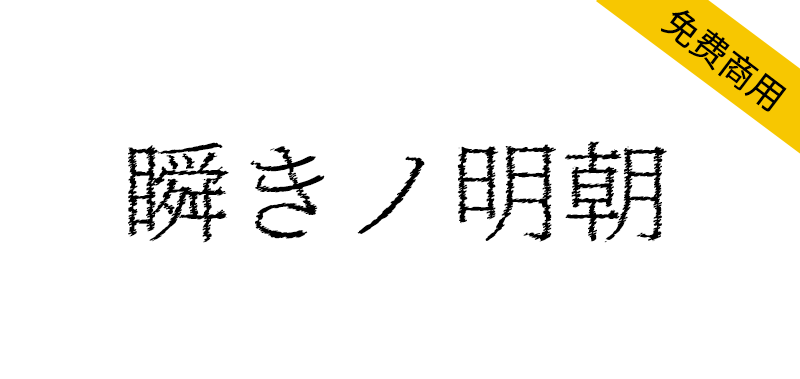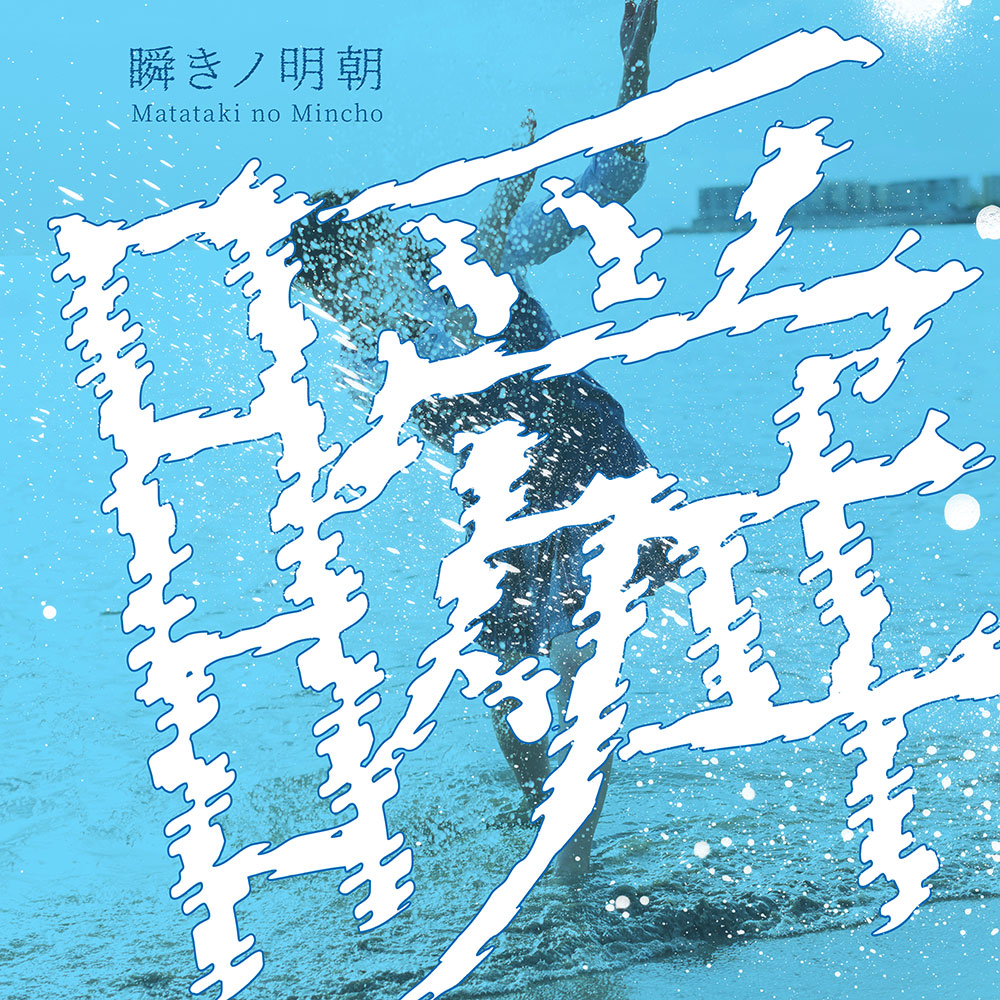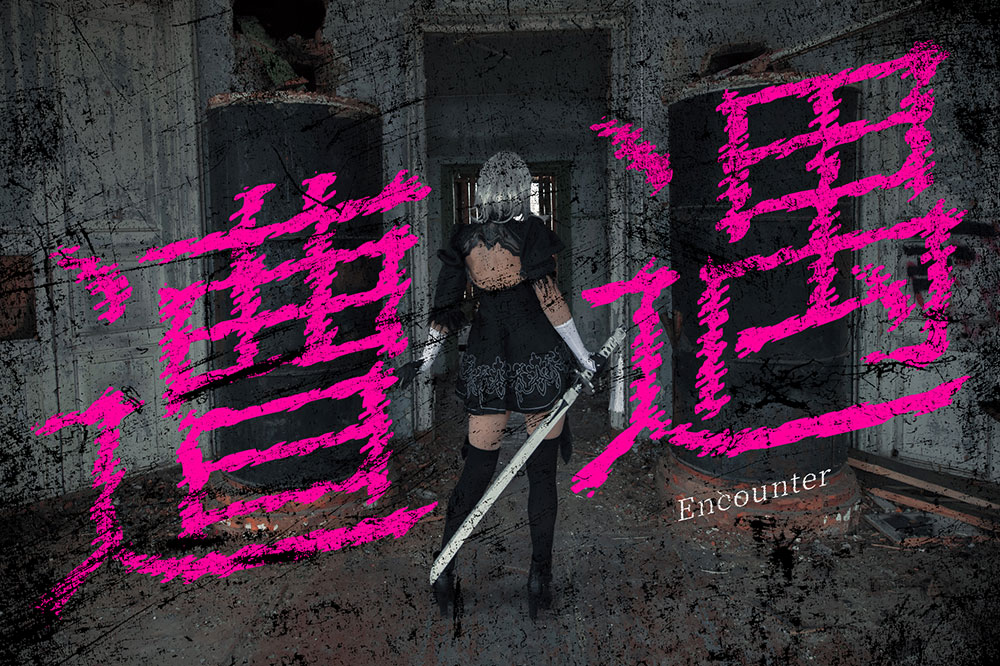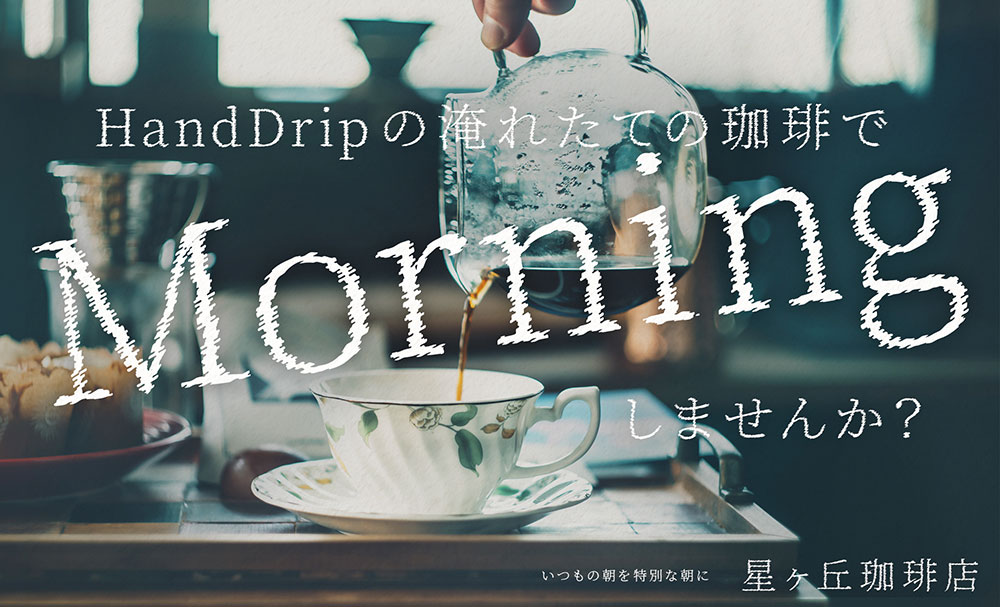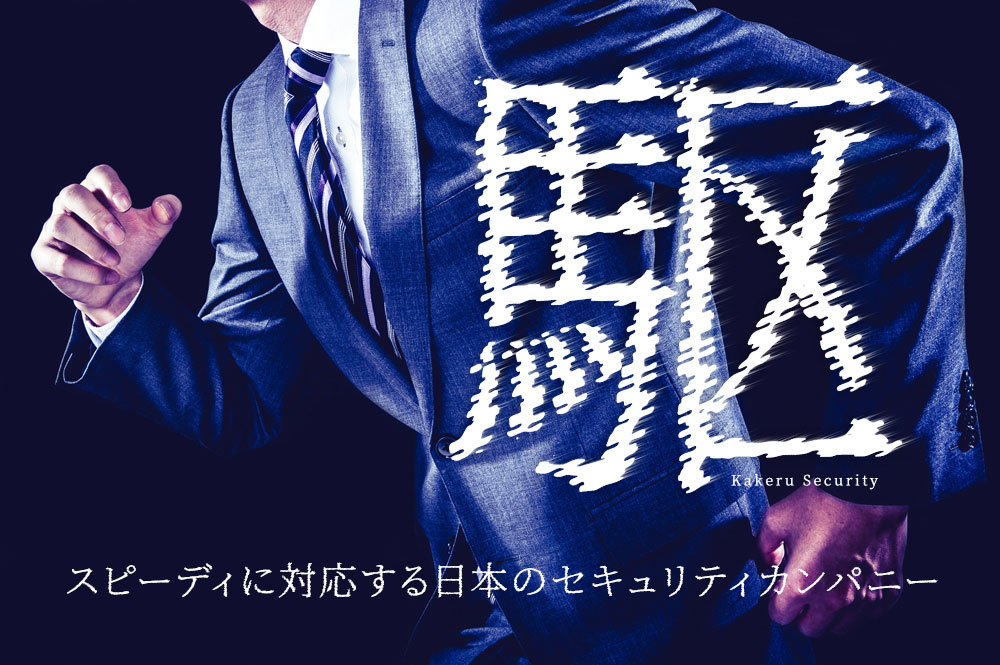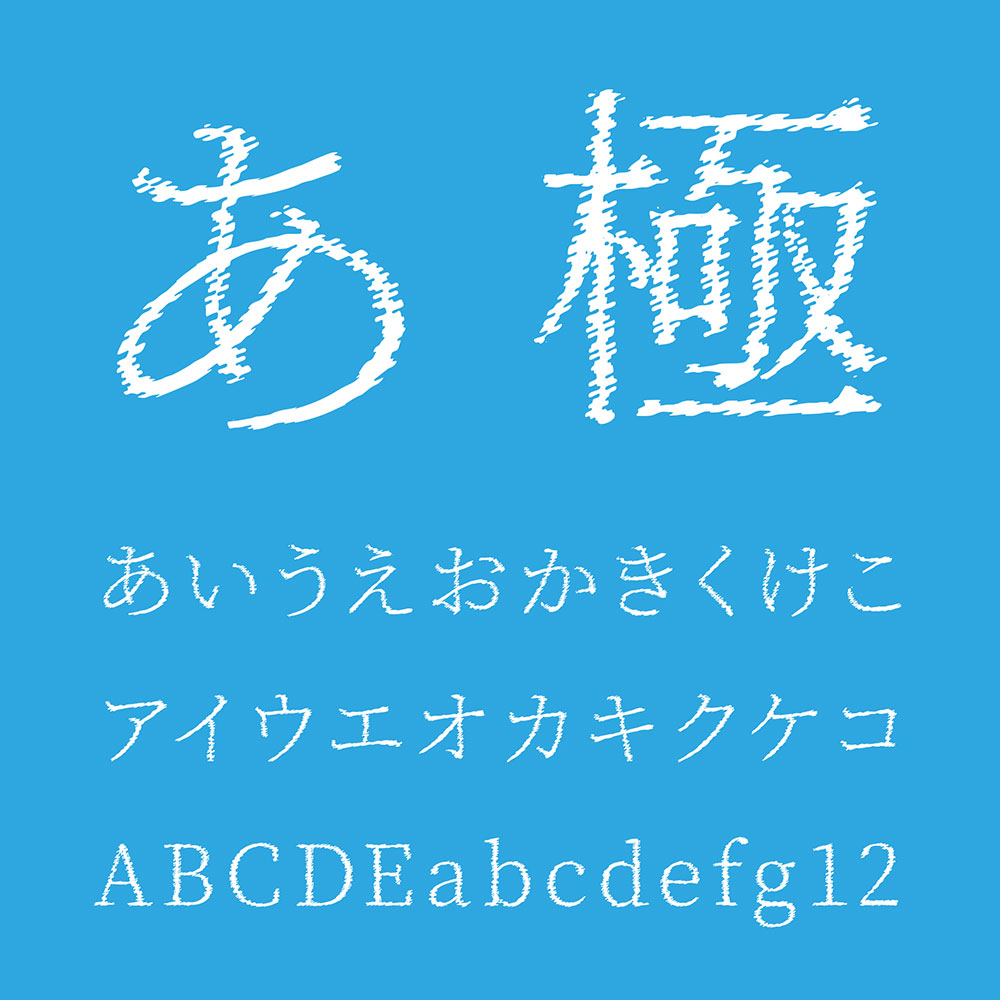
【瞬きノ明朝】一种锯齿状摇摆的具有冲击力的字体
谁说宋体只能端庄典雅?瞬きノ明朝彻底颠覆你的认知!这款基于思源宋体的字体,以锯齿状的摇摆姿态带来撕裂般的视觉冲击力,专为打造吸睛标题而生。更棒的是,它采用SIL OFL 1.1授权,可完全免费商用,让你毫无顾虑地挥洒创意,轻松让设计脱颖而出。
【瞬きノ明朝】一种锯齿状摇摆的具有冲击力的字体
瞬きノ明朝(またたきのみんちょう)是基于“思源宋体”制作的一种锯齿状摇摆的具有冲击力的字体,非常适合用于标题、标志的设计场景。
【瞬きノ明朝】一种锯齿状摇摆的具有冲击力的字体